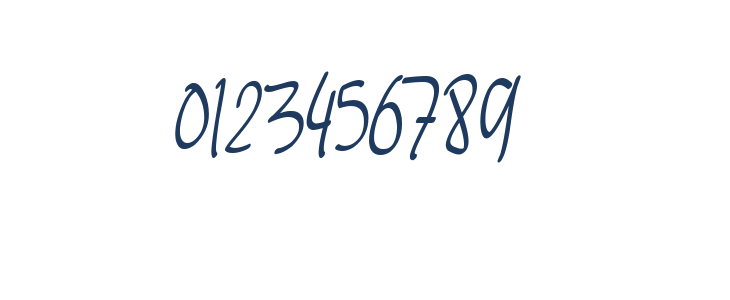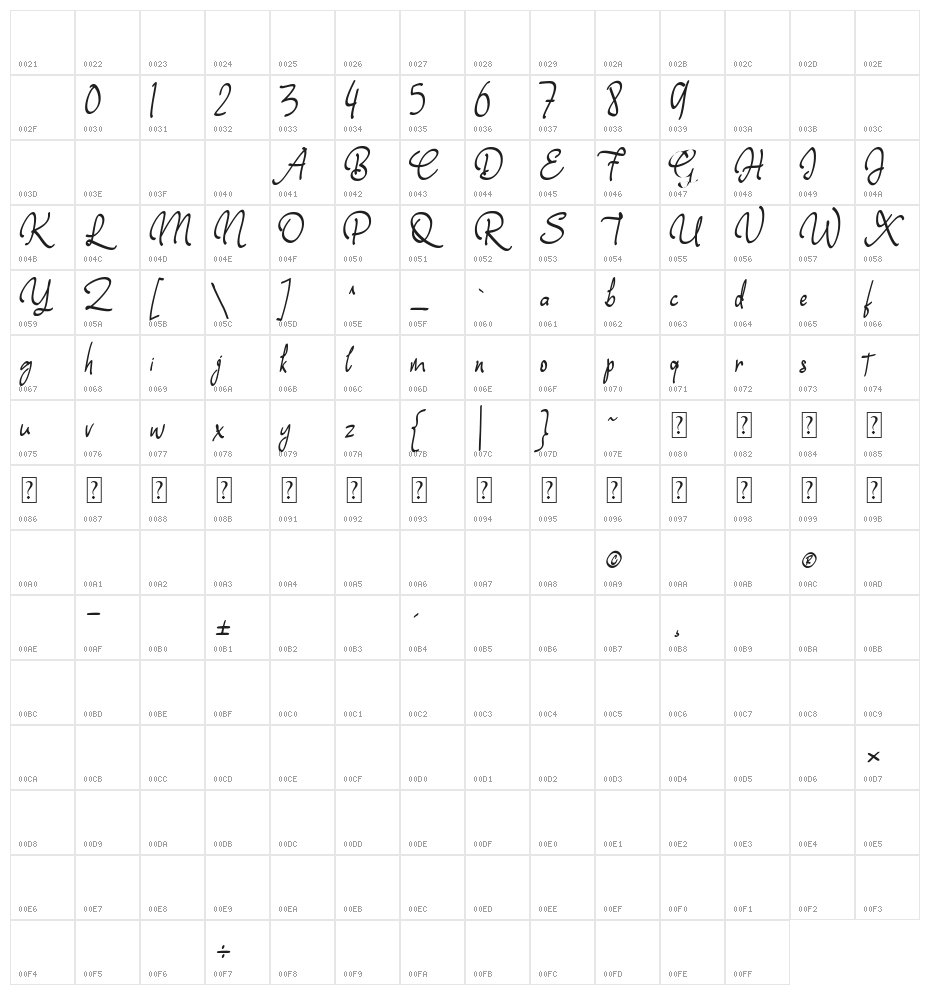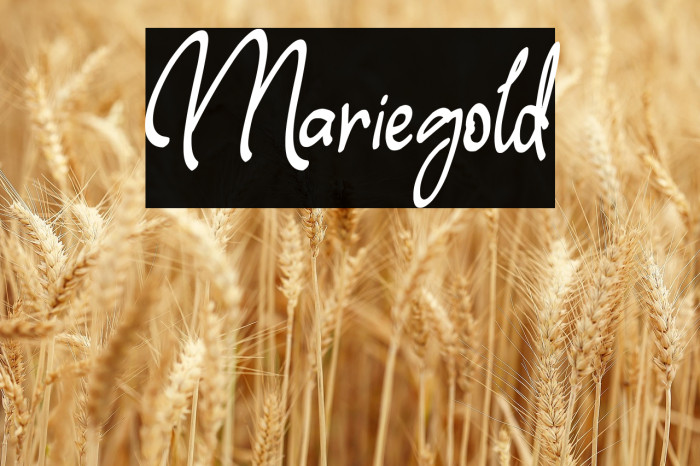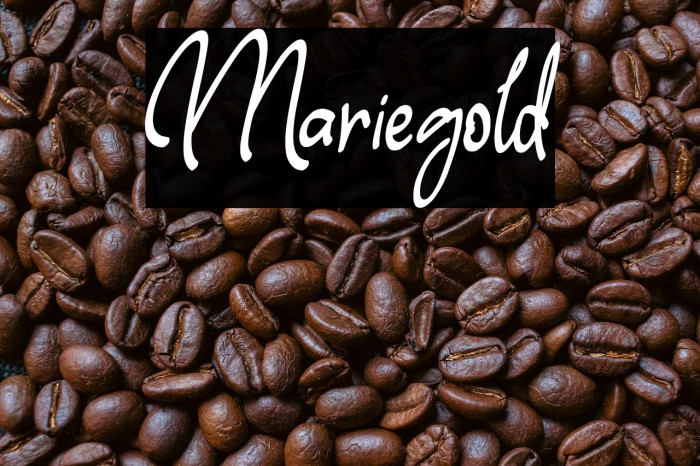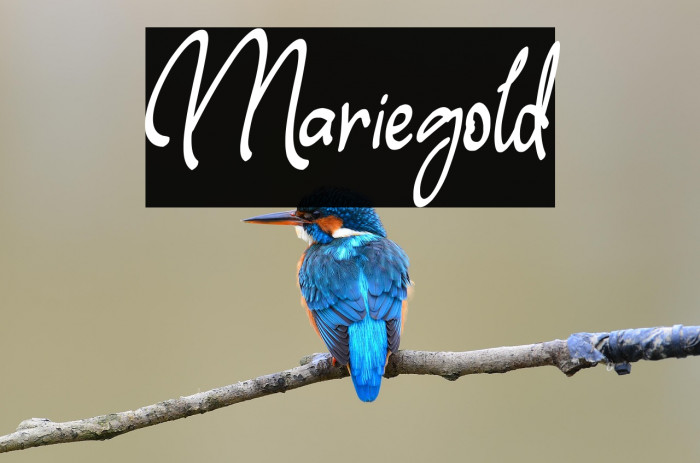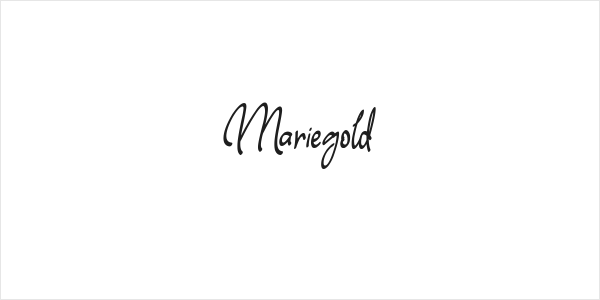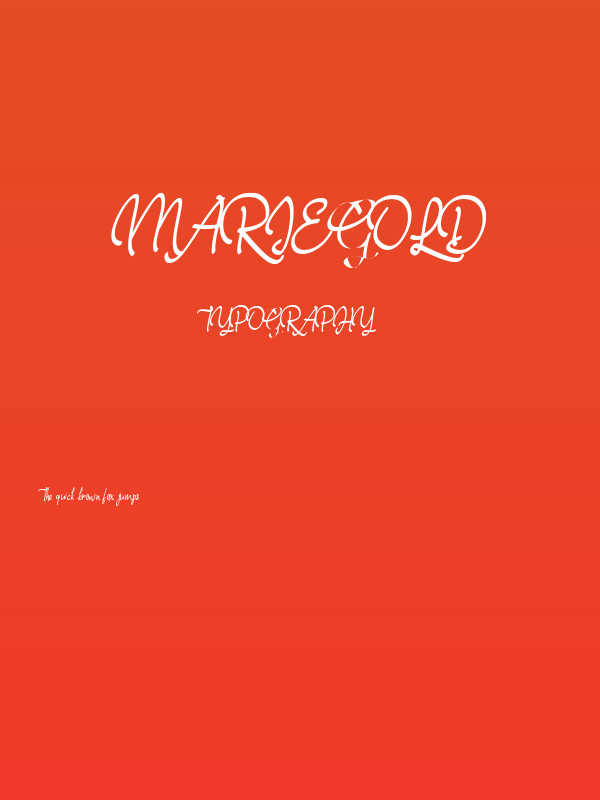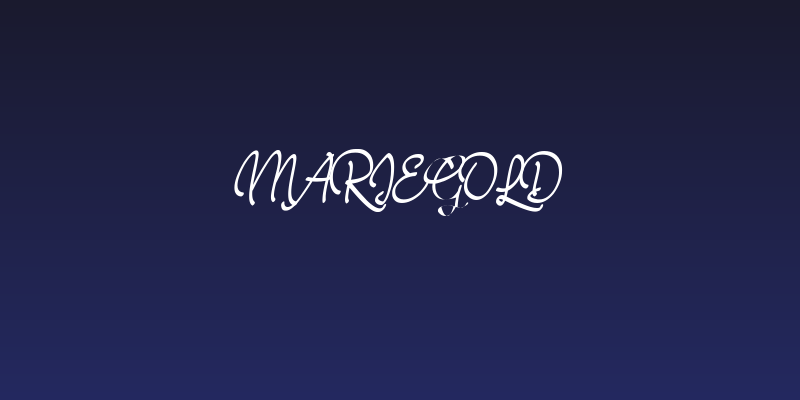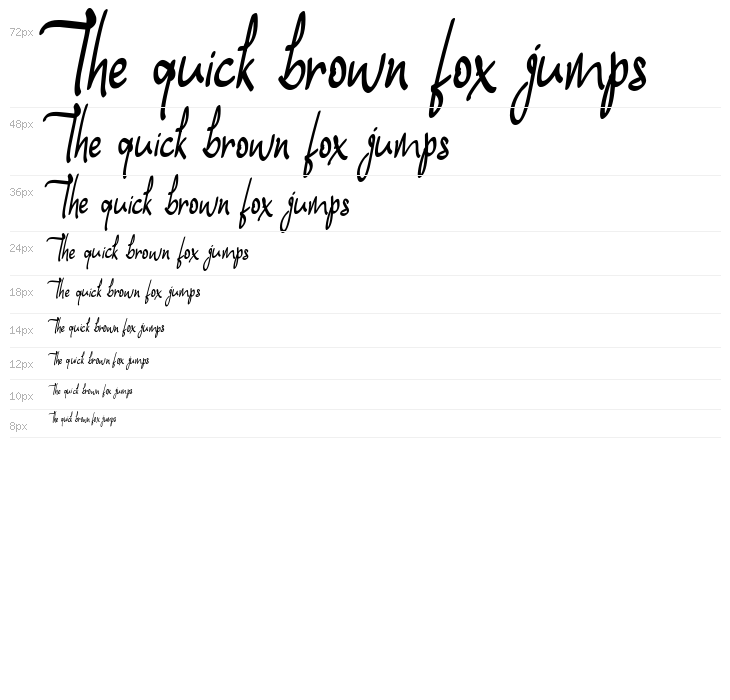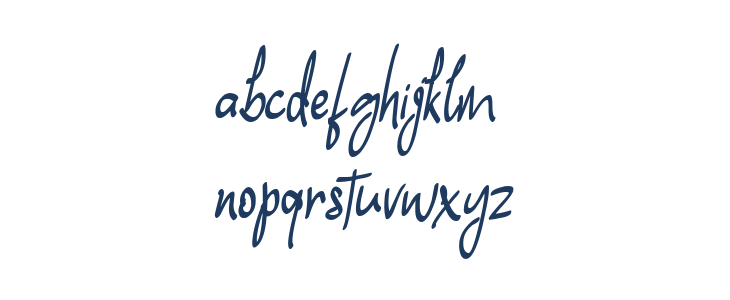
Mariegold Font
| 整体风格 | Elegant, Sophisticated |
| 使用场景 | Logos, Invitations, Branding |
| 推荐项目 | Ideal for wedding invitations, luxury branding, elegant stationery, and high-end product packaging. |